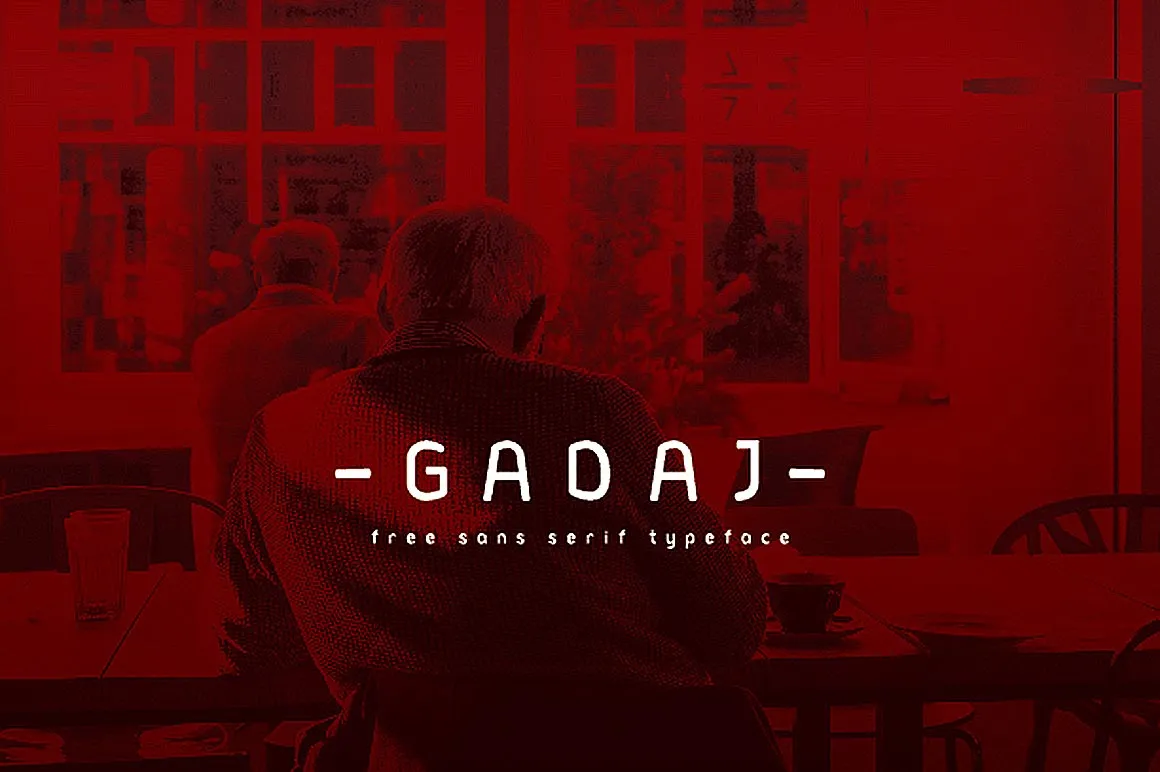
Gadaj Font – Fonte Grátis
Gadaj Font
A fonte Gadaj é uma elegante escolha para projetos criativos, especialmente quando você procura algo moderno e sem serif. Originária do trabalho incisivo de Przemyslaw Zieba, ela traz um toque fresco e versátil que combina perfeitamente com seu estilo de design atual. Ideal para ambientes digitais dinâmicos ou projetos de gráfica que exigem uma aparência minimalista e futurística, Gadaj é o parceiro perfeito para quem busca alegria em cada linha e espaço vazio entre letras. É certamente uma fonte sans serif para adicionar brilho aos seus próximos trabalhos, tanto em textos quanto em logotipos. Com sua simplicidade e facilidade de uso, Gadaj é um verdadeiro talento na categoria de fonts sans serif. E para aqueles que acreditam que design deve ser uma expressão da alma, esse é o font que você precisa.